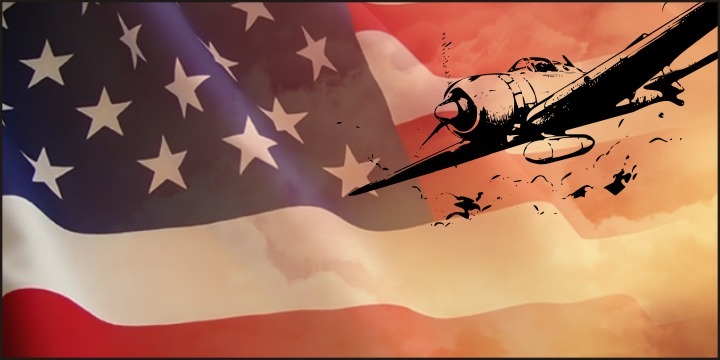
WarIIWarplanes di Intellecta Design è un font gratuito di dingbat militari, basato sulle silhouette degli aerei della Seconda Guerra Mondiale e su scene di aviazione abbozzate. I disegni ricordano le illustrazioni d'epoca: aerei a elica in virata, angolati per dare l'idea del movimento, con linee d'inchiostro ruvide e dettagli di sfondo leggeri che rendono il set dinamico e mai statico.
Questo font gratuito è perfetto per poster, menu di giochi, packaging di modellini, riviste di storia ed eventi grafici in cui vuoi inserire immagini di aerei senza ricorrere a illustrazioni separate. Funziona benissimo anche per incipit di capitoli, titoli, badge e brevi testi, poiché gli aerei aggiungono già da soli dinamismo e carattere.